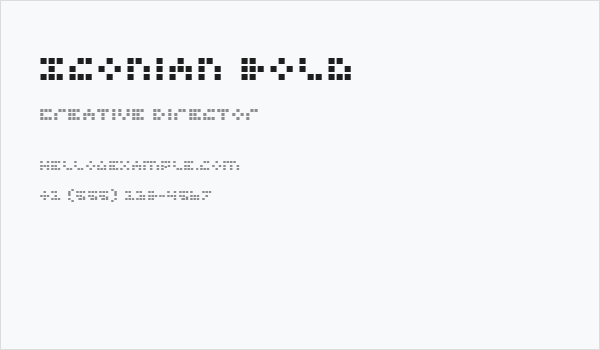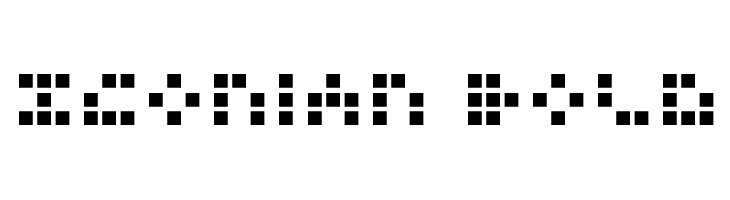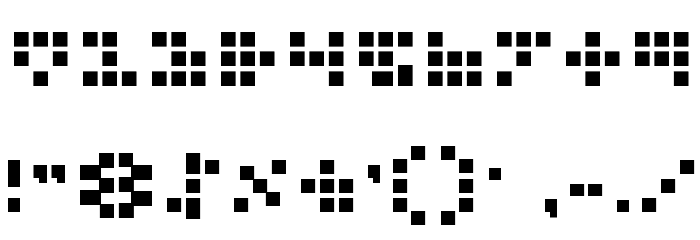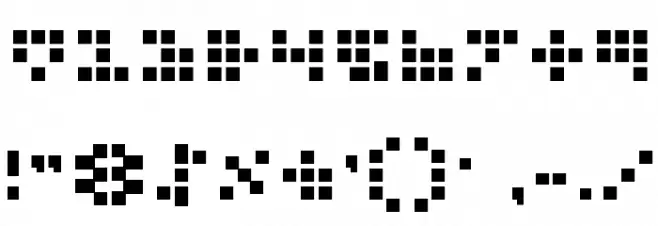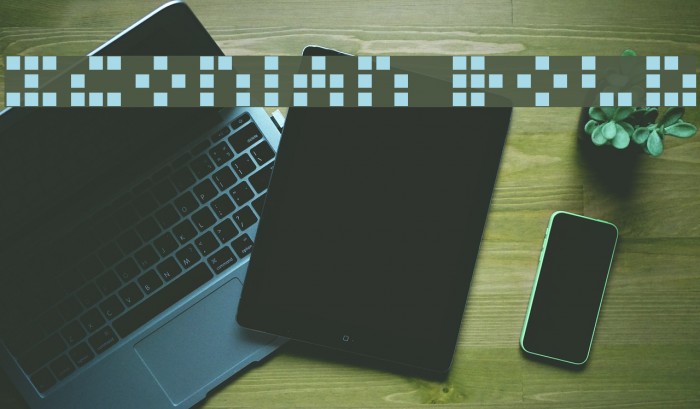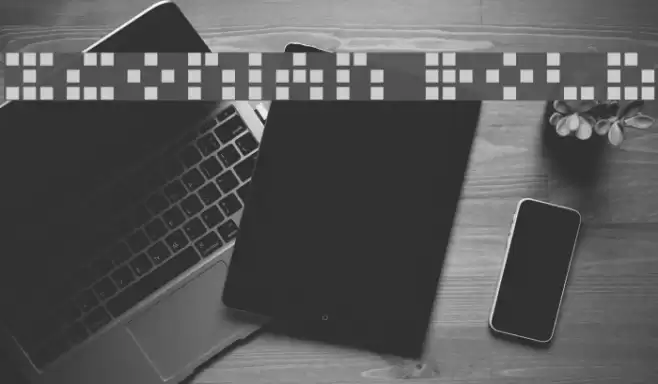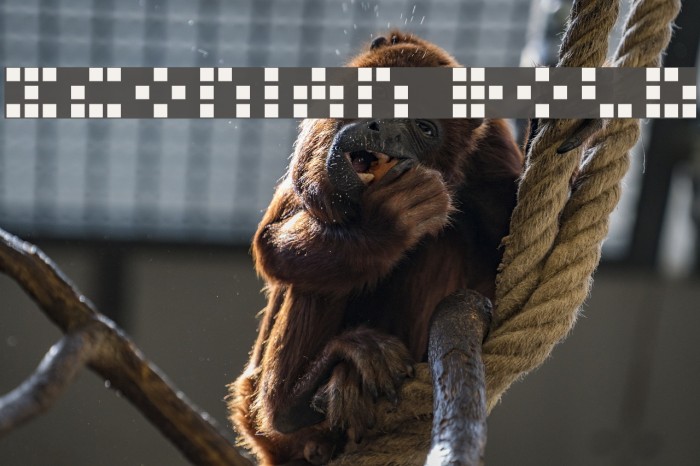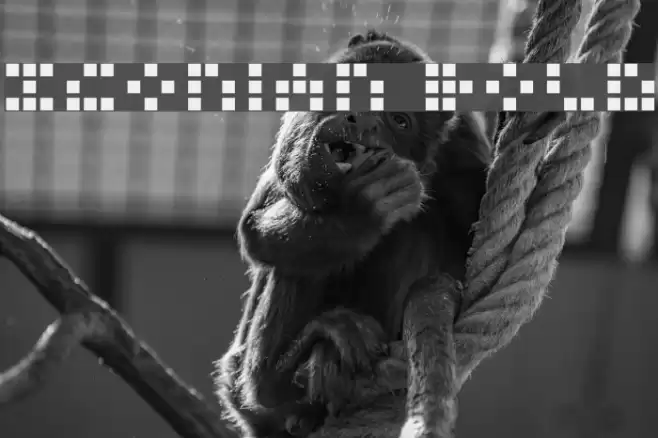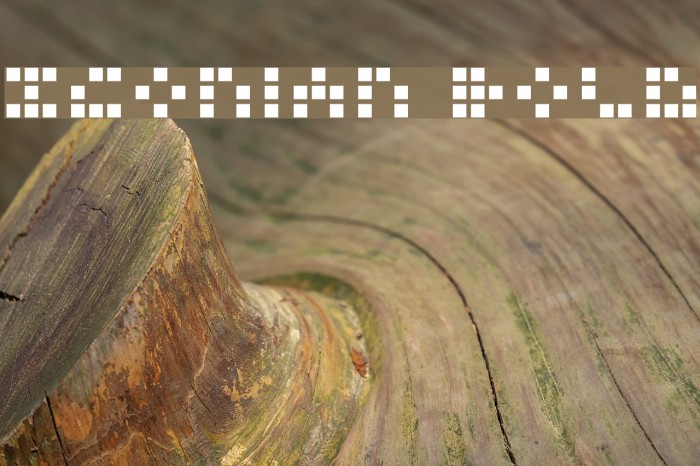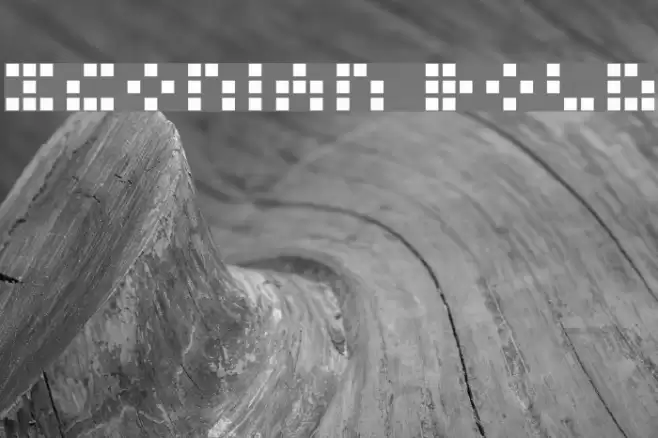
Iconian Bold Font
| Estilo general | Retro, Digital |
| Caso de uso | Logos, Headlines, Digital displays |
| Proyectos propuestos | Ideal for retro-themed designs, video game interfaces, digital art projects, and any creative work that seeks to evoke a sense of nostalgia or digital futurism. |